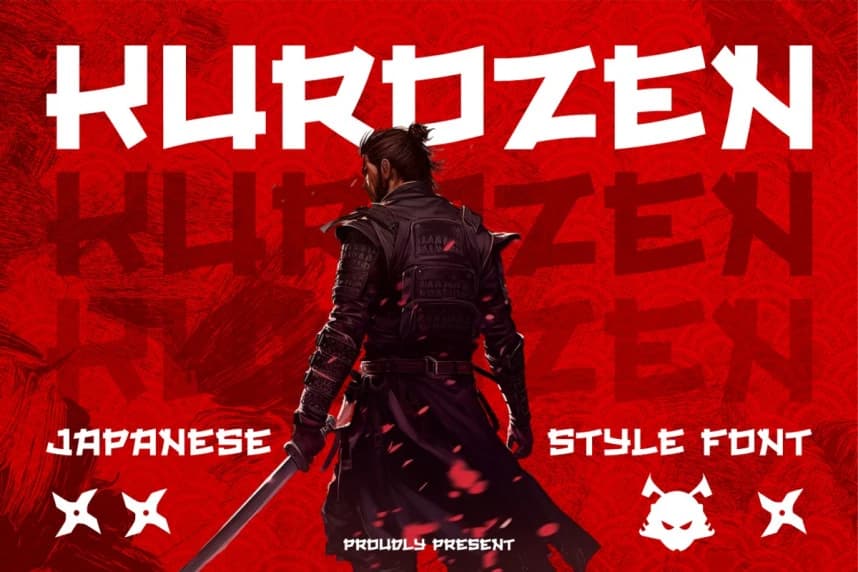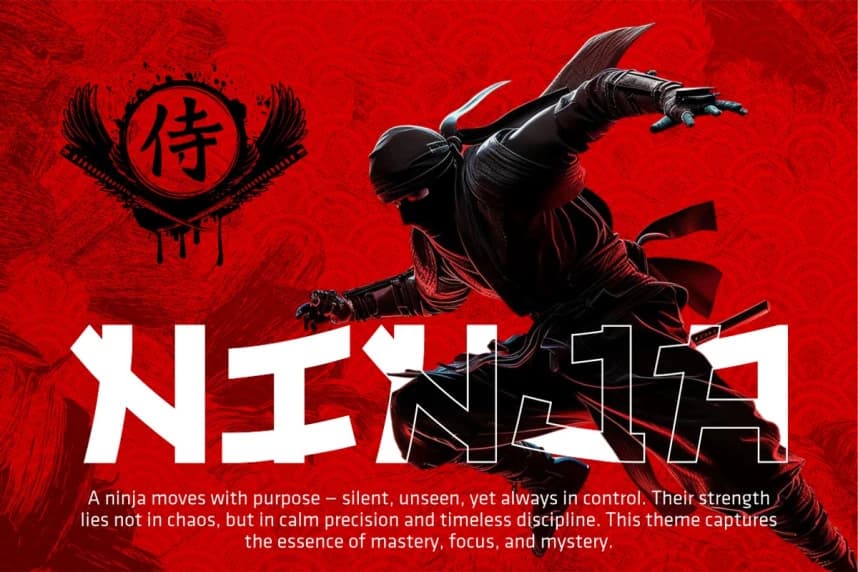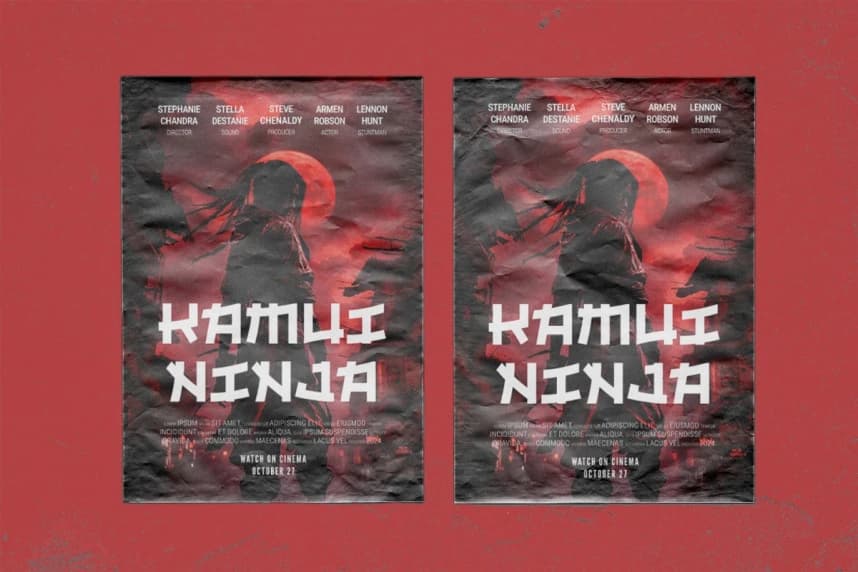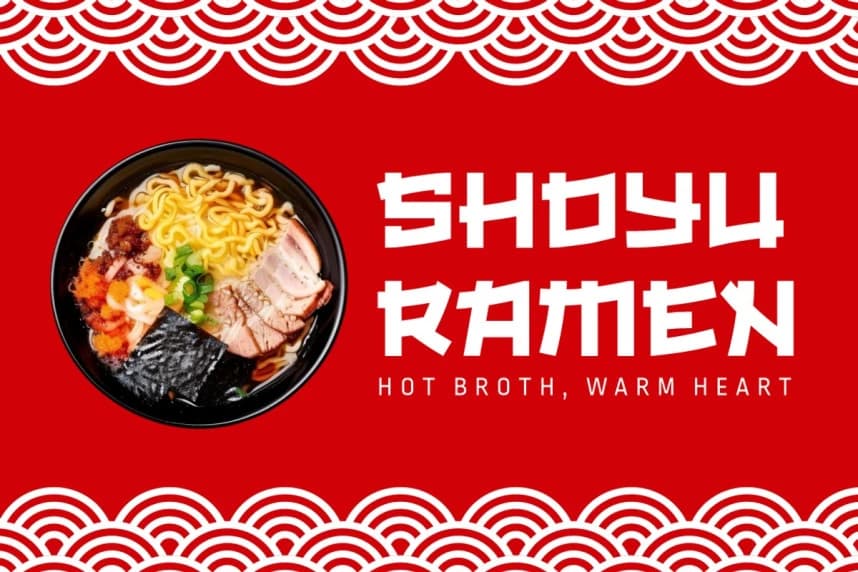
Kurozen Japanese Style Font
Kurozen Japanese Style Font, geleneksel doğu formlarından ilham alan keskin ve ifade dolu bir tasarım sunar. Her harf, kalın çizgiler, eğimli kesimler ve dinamik kenarlara sahip olup savaşçı kesinliğini yansıtır.
Kurozen Japanese Style Font, geleneksel doğu formlarından ilham alan keskin ve ifade dolu bir tasarım sunuyor. Her harf, kalın çizgiler, eğimli kesimler ve dinamik kenarlarla savaş sanatlarının kesinliğini yansıtıyor.